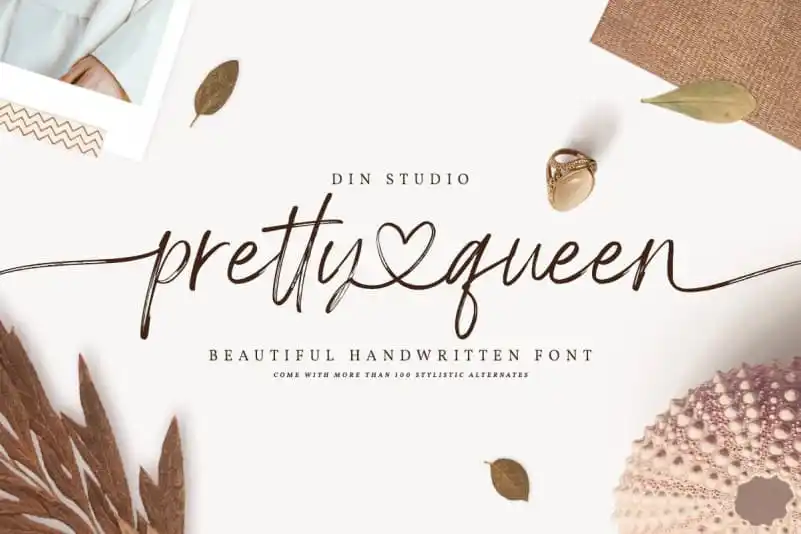
Pretty Queen Brush Font – Download Grátis
A Pretty Queen Brush Font é uma escolha perfeita para quem busca transpor a elegância e sofisticação da escrita de rainhas no mundo digital. Nessa categoria de fontes script, ela surge como um autêntico exemplar que inclui letras maiúsculas, minúsculas, símbolos e suporta múltiplas línguas. Ela traz a ligação entre palavras, alternâncias contextualizadas, alternativas estilizadas e até mesmo swashes personalizados. Dessa forma, é perfeita para qualquer projeto profissional de marca ou design gráfico que precise de um toque único e encantador. Com cada letra possuindo um toque singularmente belo, a Pretty Queen Brush Font surge como uma opção inovadora em nossa galeria de fontes.